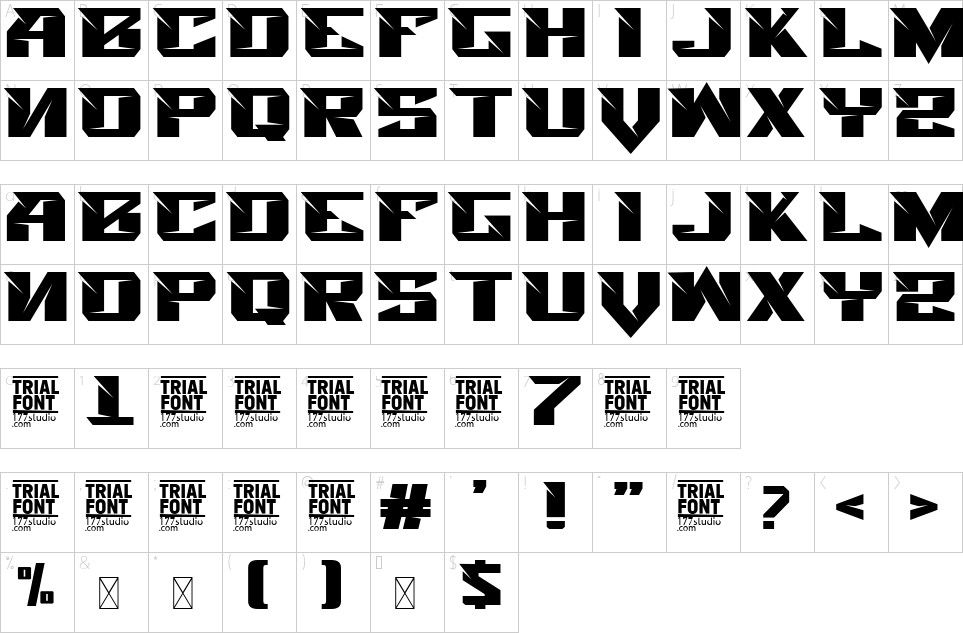
A fonte Great Sport é uma escolha ótima para aqueles que procuram uma fonte moderna e elegante para projetos gráficos variados. Desenhada pelo 177Studio.com, essa fonte é uma delícia para quem procura uma mistura de estilo moderno com uma leveza e sofisticação. Foi criada para quem adora uma fonte que se destaca sem perder o charme, perfeita para gráficos de mídia social, design editorial ou mesmo para nomes de marca. Com 2,843 downloads, é evidente que a Great Sport conquistou o coração de muitos designers que buscam uma opção de fonte de alta qualidade e estilo para seus projetos. Se você está procurando por uma fonte versátil e atraente, Great Sport pode ser a escolha certa para tornar seus projetos ainda mais impecáveis.